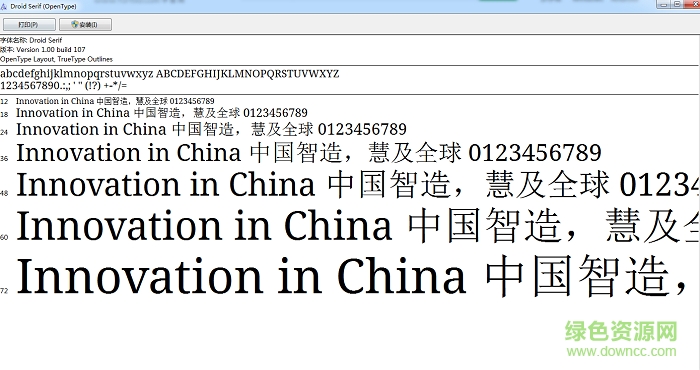
droid serif
droid serif字體是一款帶襯線粗的安卓系統(tǒng)字體,字身緊湊,筆畫粗細(xì)勻稱,清晰明快易于閱讀,適合在大段落文字中做排版,需要的小伙伴快來(lái)下載吧!
serif含義介紹
serif,意思是在字的筆畫開(kāi)始、結(jié)束的地方有額外的裝飾,而且筆畫的粗細(xì)會(huì)有所不同。中文字體中的宋體就是一種最標(biāo)準(zhǔn)的serif字體,襯線的特征非常明顯。字形結(jié)構(gòu)也和手寫的楷書一致。因此宋體一直被做為最適合的正文字體之一。不過(guò)由于強(qiáng)調(diào)橫豎筆畫的對(duì)比,在遠(yuǎn)處觀看的時(shí)候橫線就被弱化,導(dǎo)致識(shí)別性的下降。